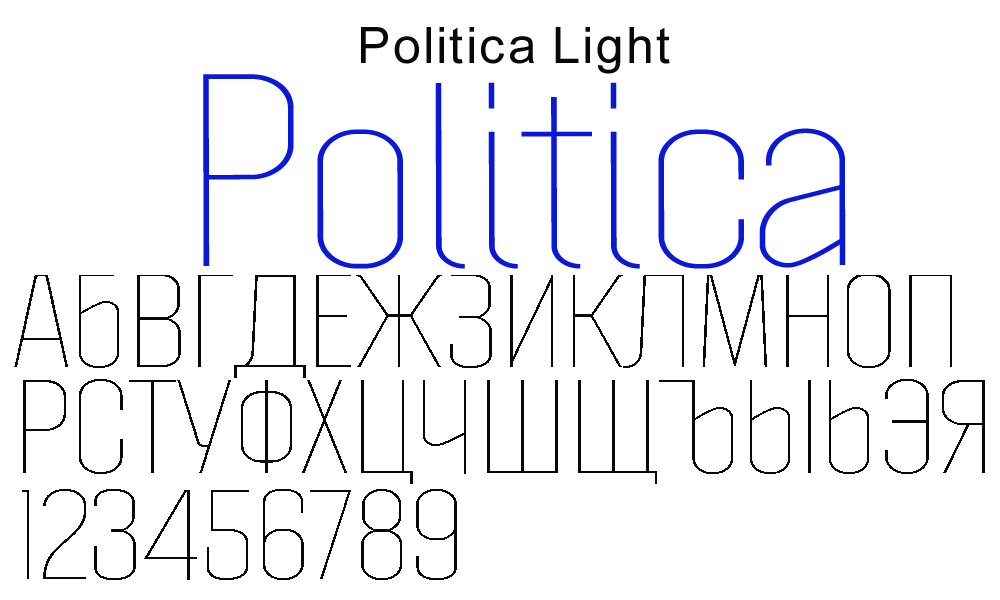
Шрифты без засечек
Разница между шрифтом без засечек и шрифтом без засечек заключается в том, что без засечек нет тех небольших декоративных линий, которые характеризуют засечки.
Без засечек, с их современным, более чистым и простым внешним видом, как правило, более доступны в интернете, поскольку они гораздо легче читать на экранах, независимо от их шрифта или размера устройства. Понятно, что без засечек являются наиболее часто используемые шрифты Google
Red Hat
Шрифт без засечек Red Hat разработан Джереми Миккелем в рамках работы по брендингу под руководством Пентаграммы.
Как и сам Linux, его можно использовать бесплатно (но с ним гораздо проще разобраться).
Public Sans
Public Sans — это бесплатный веб-шрифт с открытым исходным кодом, разработанный для интерфейсов, текста и заголовков, созданный на основе Libre Franklin и созданный в рамках системы веб-дизайна США.
Loki
Loki — это гибридный шрифт, рукописный сценарий кисти с базой без засечек и содержит довольно приятные кривые. Это один из шрифтов, которыми можно сделать заявление, особенно хорошо работает в больших заголовках.
Manrope
Manrope был создан Майклом Шаранда и представляет собой семейство шрифтов с открытым исходным кодом, которое было разработано для многократного современного использования в заголовках, параграфах, печати и в Интернете. Шрифт охватывает большинство латинских и кириллических языков.
Salt
Шрифт Salt представлен в двух видах: обычный и жирный. Он был создан Машей Чупровой и имеет «низкий центр тяжести».
Нам также нравятся иллюстрации для осьминога, используемые для его демонстрации.
Alcubierre
Геометрический шрифт без засечек Alcubierre — работа дизайнера Мэтта Эллиса. Следуя по стопам своего оригинального бесплатного шрифта Ikaros, этот чистый, минимальный шрифт работает для различных целей.
Big John / Slim Joe
Big John был создан дизайнером Ионом Лучиным, которым поделился им на Behance, а затем добавил ультралегкий родственный шрифт: Slim Joe. Оба шрифта являются заглавными, и отлично сочетаются друг с другом. Эти шрифты идеально подходят для заголовков и заголовков.
Titillium Web
Бесплатный шрифт Titillium создан в рамках проекта шрифтового дизайна в итальянской Академии искусств Урбино. Каждый учебный год студенты работают над проектом, развивая его и решая проблемы.
Atami
Atami — экспериментальный шрифт. Он поставляется в двух разновидностях и трех стилях, и идеально подходит для создания плакатов и логотипов.
Chivo
Chivo — это гротескный шрифт, который идеально подходит для заголовков и оформления страниц, чтобы привлечь внимание. Уверенный и элегантный, имеет различные курсивы.